香港地铁宋:观察、再用与再生
无论品牌还是站内路牌,港铁一系列中英双语文字设计(Chinese-English bilingual typography)自1979年通车起便世界知名。其中对明体的广泛运用,至今也特立独行于其他汉字使用国家。港铁明体嫡传统为什么当年的地铁公司选用明体作为主字体呢?就这笔者曾经问过恩师、也是当年地铁公司开创初期内部设计师之一的柯炽坚(Sammy Or)老师,他表示已不可考。但是这一决定延续至今成为一优良设计传统,却是值得我们去细看观察。与地铁合并成港铁前的九广东铁,也有使用明体嫡传统。1980 年代电汽化后,港铁的站牌一律更改成“白底黑字”,字体则用上结构较方正、笔画圆润肥厚的明体,至今在大学站洗手间、或新界沿线部分老站的标牌可以看到。其至九十年代初风格转向“蓝底白字”、后期又聘请英国 Dalton Maag 公司设计无衬线西文字体 Casey,最终在两铁合并敲定下跟随地铁公司的设计归为同一套品牌、路牌法则。明体在品牌、路牌运用的好处近年黑体大行其道,大众追求现代与新颖感,明体古雅、友善的优点在三地一直被大众忽略。明体长期欠缺新的风格和表情,又受“新细明体”“老宋”“匠体字”等负面印象的影响,其天分一直被埋没。事实上,明体造型出众、笔画的粗细与汉字造形天生便相配;粗细对比所营造出的版面表情,也比黑体有趣而吸引人。在印刷品上,明体内文字重适合内文编排,粗体则可以用在语气僵化和标题之上,营造优雅的文化氛围。在路牌上,除观感优雅外,优良的明体设计能够提供高辨认性,笔画粗细的变化可以抵消路牌背光所造成的光晕错视,要比黑体更清晰、更好辨认。“地铁宋”是一个模糊概念笔者曾有朋友慕名而来拍摄“地铁宋”的照片,但“地铁宋”在今天却是一个模糊概念。笔者单在金钟站已经拍到四套分别属于不同字体家族的“宋体”。从历史看,地铁也从来没有一套固定的明体在用。近期被纳入“地铁宋”范围的,计有:
华康俪宋体
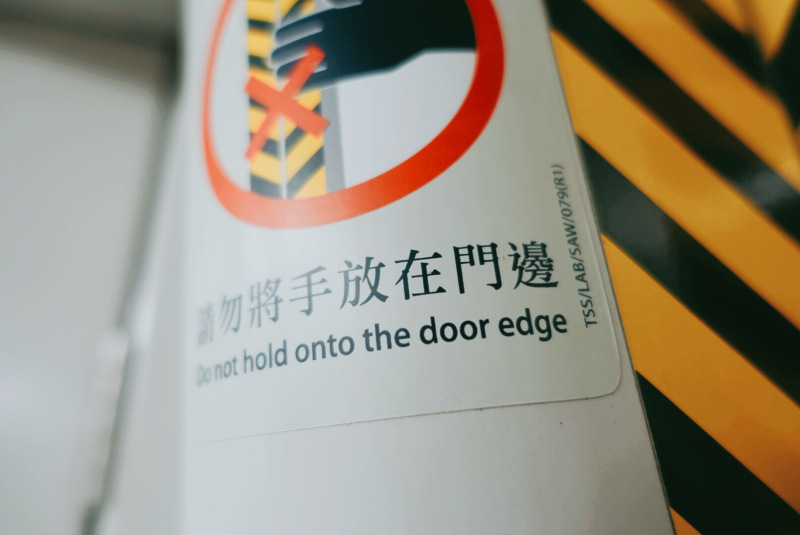
车门旁边“请勿将手放在门边”的俪宋体警告字句。
以俪宋体编排的致歉告示。
无论品牌还是路牌主要字体,港铁新的印刷出品都已经转换成“俪宋体”。“俪宋体”是柯炽坚的在1980年代末开发、全球第一套完全由PostScript技术开发而成的中文字体;港铁现用的中字重(Medium)于 1990 年代中期由华康推出发行。“俪宋体”的设计概念强调空间结构匀称、“行气”强(一气呵成感)、笔画圆润,像卫夫人“坠石”形容的水滴式点划,营造出一种高度中性感觉,基本适合何用途使用。圆润的外表恰巧可以将路牌光晕抵消,加上造形中性,放在港铁站牌上竟有一种刚好的感觉。
蒙纳宋体
“用心扩展铁路建设更好香港”一段为蒙纳宋体。“蒙纳宋”是最新加入“地铁宋”阵营的明体,于 1980 年代初期、也是由柯老师领导香港蒙纳字体公司开发。“蒙纳宋”日常多见于港府公文、报纸杂志等印刷刊物。港铁多将“蒙纳宋”用于站内楼梯贴纸、或个别维修、更新标示,与“俪宋体”混用。“蒙纳宋”的根源,来自俗称“上海宋”、由上海字模一厂于 1960 年研究发的金属活字字稿。笔画由柯老师更改成适合香港字体规范使用的部首。最突出的,莫过于粤语俗称“撑艇仔”的楷化“走之底”部首,乃柯老师首创。港铁沿线月台金属字
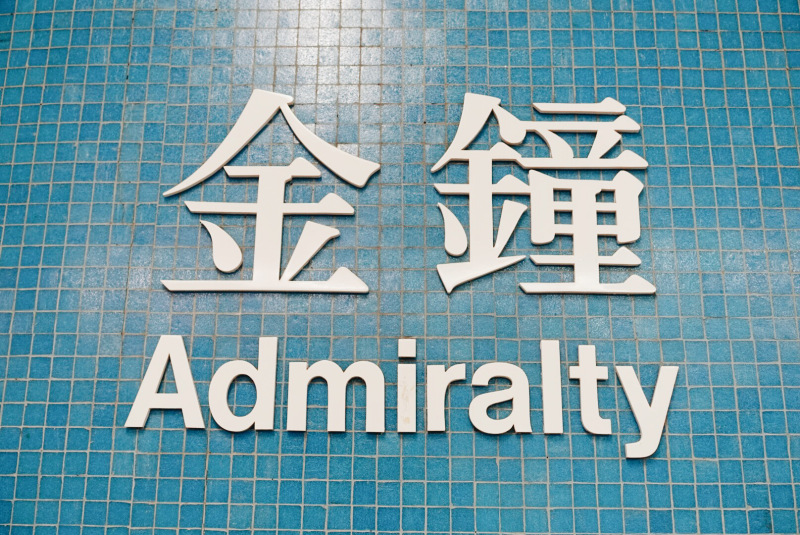
柯炽坚老师设计、修改的金属字牌。港铁沿线月台的金属字是柯老师在地铁公司工作时修改照相排字字体而成的作品。1970 年代末电脑还未有普及,PostScript 技术还未发明,当时在香港通用的照相排字字体并没有可以放大成月台柱子上适用大小的字体可用,加上需制作香港地名用字,作为公司内设计师,柯老师便根据康熙字典笔画标准,亲手修正日语明朝体字体的笔画,横划的粗细也是下苦功之处。部分字体横划的小三角近乎变形成圆形,是照相排字机将字体过分缩放的印记。柯老师并不满意这作品,却为今天香港人、游客所津津乐道的设计。真正的“地铁宋”?观察中,也发现“地铁宋”有着其他变体,结构风格也与柯老师的设计不同。
不知道其实际名称下暂以数字命名之:
地铁宋(一号)
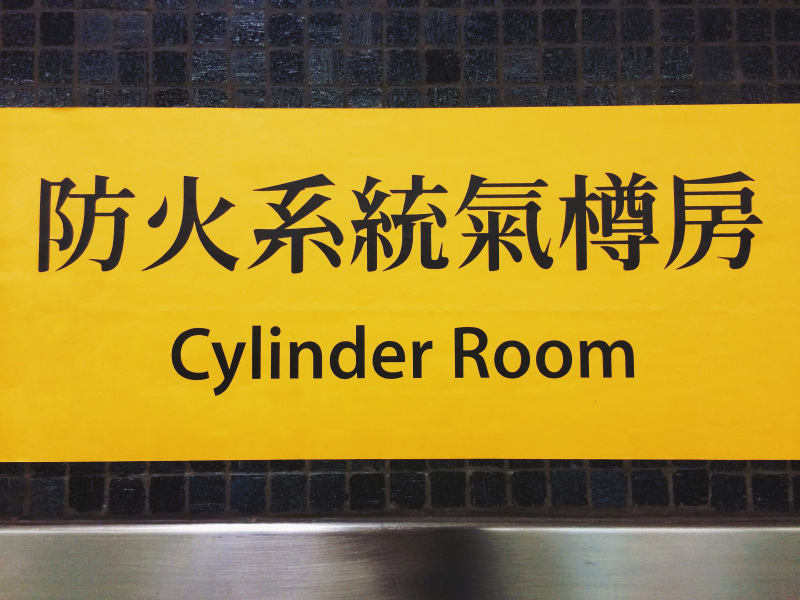
观塘沿线的“地铁宋”(一号)。可见“统”字的竖横勾画、“樽”字的直钩较圆润有肉。“地铁宋一号”该是最为一众地铁列车迷、香港人所津津乐道的设计,也是传说中的“MTRSong”字体。勾画尖锐锋利,回笔处设计夸张、爽直而具设计感,风格出众。“地铁宋一号”是为标题用途而生的明体。这设计至今我们还可以在观塘线一带月台墙身的警告字样偶然看见。由于“地铁宋一号”是照相排字字型,除了今天使用十分困难外、缺字也是一大问题。所以港铁近年已取俪宋与蒙纳宋方便制作,逐步废弃“地铁宋”一号。
地铁宋(二号)
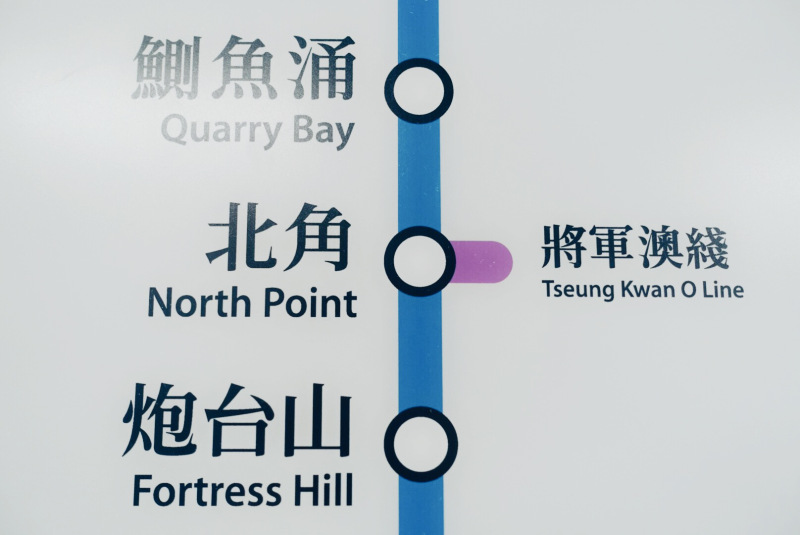
笔者最喜欢为“地铁宋”(二号),感觉很能代表香港的性格。
“地铁宋”(二号)。
“地铁宋二号”是一号的变体。其特色为比一号更为刚硬,去除无谓的修饰,也是笔者的心头好。“二号”多见于港岛线、东涌线一带玻璃幕门顶上的路径指示,以及旧英制车身内的路径指示灯跟贴纸标记。
地铁宋(三号)
较有书法影响的“地铁宋”(三号),可留意其点划跟直勾画。“地铁宋三号”笔画圆润、充满书法感,无论点划、直钩笔画都带有墨水造形,表情与“地铁宋一号”相近,笔画风格却完全不同。“地铁宋三号”没有特定出现地点,笔者至今发现多出现于垃圾桶标记、幕门前贴上地上的警告纸,用途相对较飘忽。资料补充:明体 vs 宋体?明体与宋体是 100% 相同的字体风格,只是称呼习惯上的分别。明体的称呼来自日本对这一类横细直粗、造形方正的“明朝体”称呼。“明体”的风格来自明代“匠体字”,刻字匠们为加强制作效率,所以将横直笔画统一粗细,方便克制。这无论在造形风格指事、还是历史指事也更适合。在中国,则自清代民间便早有约定俗成称呼这种横细直粗风格为“老宋”,直至六十年代大量造字,制作出宋一、宋二体标准字,便正式定名这风格为“宋体”,指事这字体的最远来源:宋。可是,这称呼在逻辑概念上有谬误。宋代的雕板书体,无论制作方式、风格跟性质也与“宋体”迥异,要称呼“明体”为“宋体”无疑是忽略了由宋雕板至明代“匠体”一段变化期。